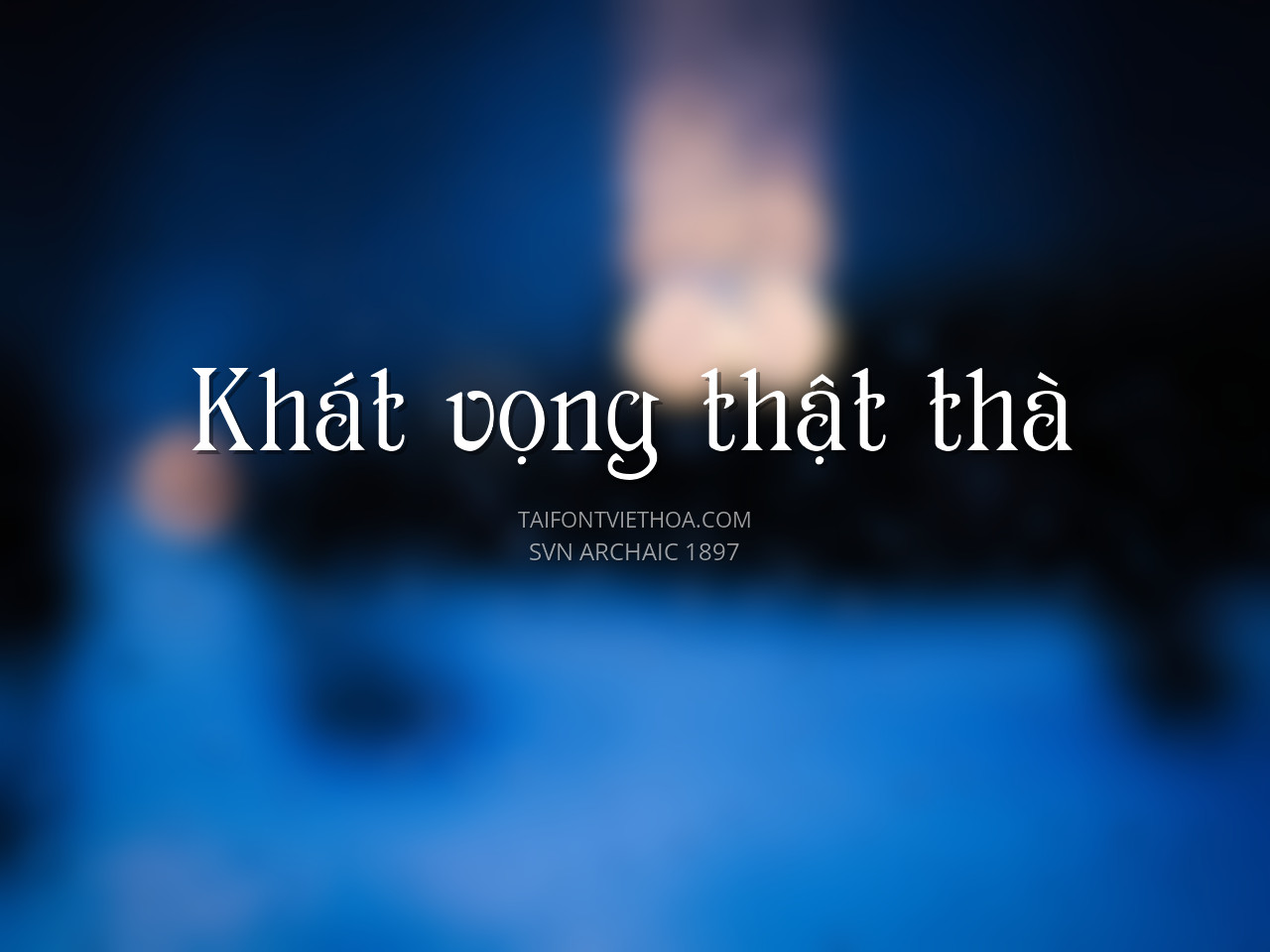
Giới thiệu về font SVN Archaic 1897 – Kiểu chữ serif cổ điển, đậm nét và trang trọng
SVN Archaic 1897 là phiên bản Việt hóa của font Archaic 1897 – một kiểu chữ serif mang phong cách cổ điển, đậm nét và rất trang trọng. Font được thiết kế với các nét chữ rõ ràng, sắc nét và cân đối, tạo nên vẻ đẹp truyền thống và chuyên nghiệp, phù hợp cho các dự án thiết kế thương hiệu, in ấn và truyền thông cao cấp.
Phiên bản Việt hóa của SVN Archaic 1897 đã được Taifontviethoa.comchăm sóc kỹ lưỡng, hỗ trợ đầy đủ dấu tiếng Việt cùng hơn 80 ngôn ngữ khác. Font giúp các nhà thiết kế dễ dàng áp dụng trong nhiều lĩnh vực đa dạng mà vẫn giữ được vẻ đẹp cổ điển và sang trọng.
Thiết kế serif cổ điển – Ứng dụng rộng rãi trong thương hiệu và xuất bản
SVN Archaic 1897 sở hữu cấu trúc serif với các nét chữ đậm, sắc nét và độ tương phản hài hòa. Font phù hợp cho đoạn văn bản dài và tiêu đề, giúp tăng tính thẩm mỹ và sự trang trọng cho thiết kế. Phong cách của Archaic 1897 mang đến sự truyền thống và bền vững cho mọi sản phẩm thiết kế.
Ứng dụng lý tưởng: thiết kế nhận diện thương hiệu, bìa sách, tạp chí, brochure, thư mời, danh thiếp và các ấn phẩm quảng cáo cao cấp. Ngành nghề phù hợp: thời trang, mỹ phẩm, nội thất, giáo dục, xuất bản và các thương hiệu định vị theo phong cách cổ điển, trang trọng.